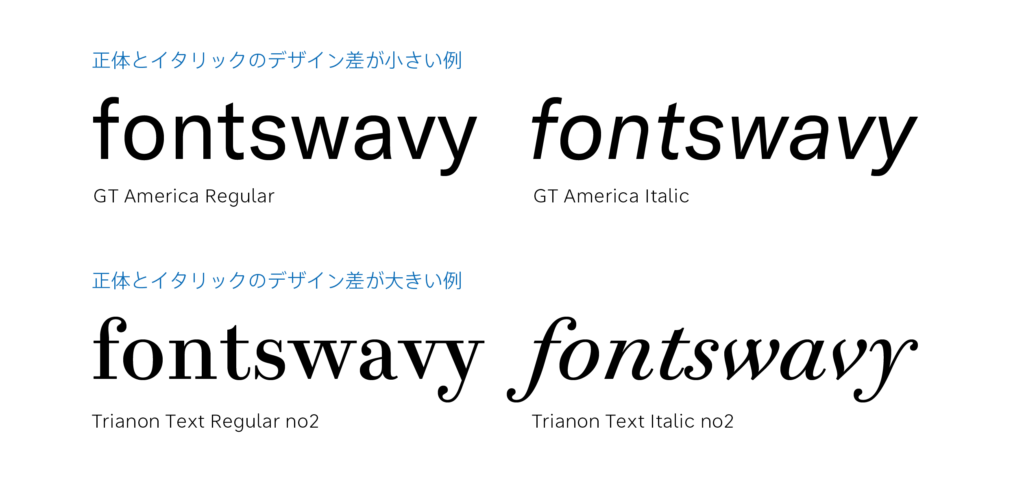
欧文イタリック03「イタリックのデザイン」
イタリックのデザインは正体をほぼ機械的に傾けた様なものから、正体よりもかなり有機的で動きのあるものまで様々で、書体の用途や想定する使用場面によって正体とイタリックのデザイン差の大小が異なります。
本文用書体の正体は長文で組まれることを想定している為、デザイン性よりも読みやすさが優先されることが多いですが、イタリックは数文字から数行程度の量で組まれることが多く、デザインの自由度も比較的高いです。
その為、イタリックはファミリーの中でその書体の個性をより強く押し出せるアイコン的な立ち位置にも成り得ます。